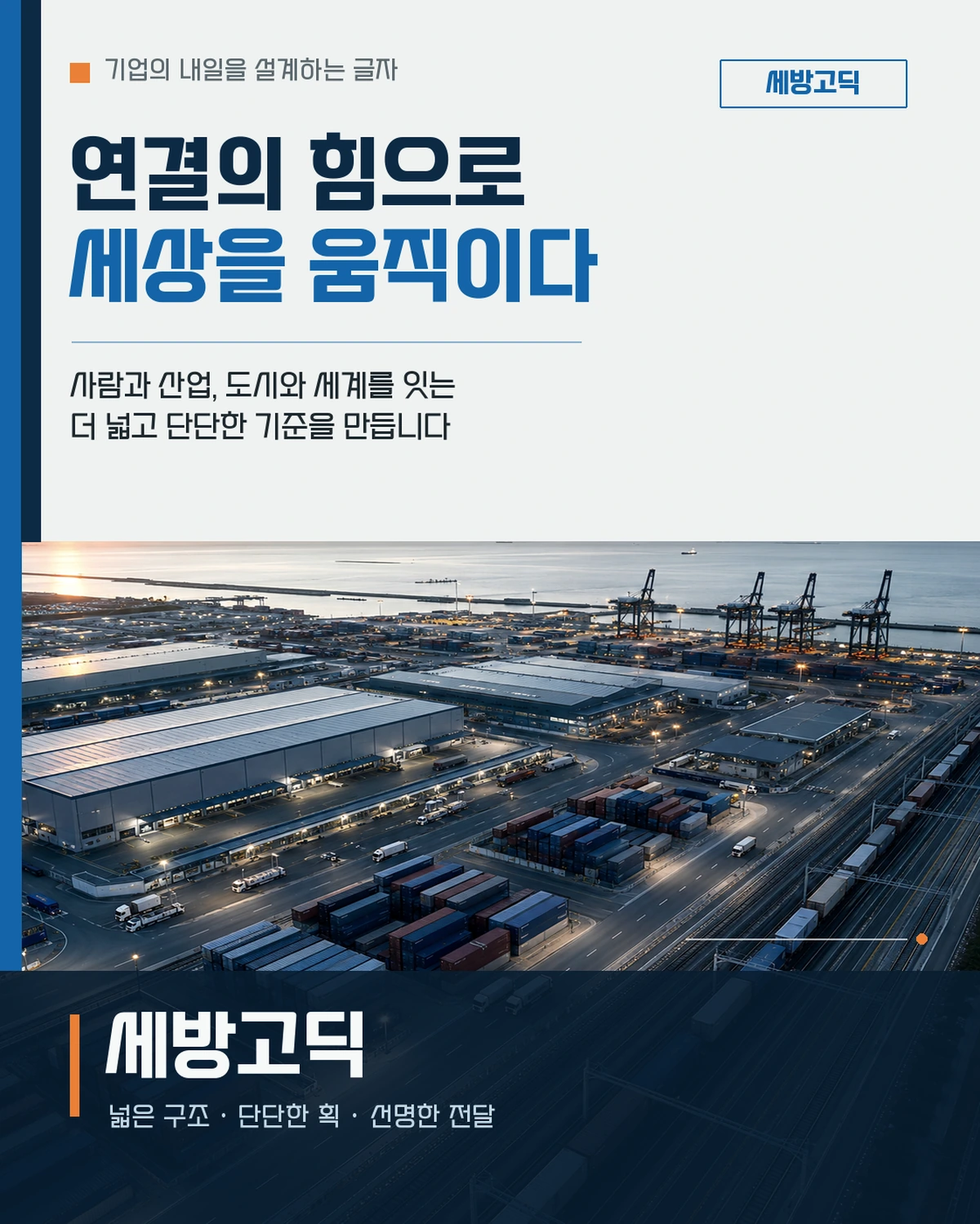
세방고딕 2.0 — 세방그룹에서 배포하는 무료 폰트입니다. Light부터 Bold, 이탤릭까지 갖춘 자면이 큰 네모틀 고딕체
세방그룹이 2020년에 처음 공개한 세방고딕을 다듬어 2026년 9월 2.0으로 새로 내놓았습니다. 기존 정체성은 그대로 두고 실무에서의 완성도와 활용성을 높였다고 밝히고 있습니다.
바뀐 점은 네 가지입니다. 초·중성에 쓰일 때 도드라지던 된자음(ㅆ·ㅉ)의 형태를 다듬었고, 단단한 인상에 섬세함을 더할 Light를 새로 만들었습니다. CI 로고의 기울기에서 출발한 12도 이탤릭과, 스페인어 같은 라틴 문자 언어를 위한 라틴 문자 128자도 더했습니다.
파일에서 재어 보면 받침에 따른 높이 차가 거의 없는 네모틀에 자면을 넉넉히 채워 인상이 단단합니다. 한글 11,172자를 모두 담았고, 세방그룹은 Light를 가벼운 본문에, Regular를 보고서에, Bold를 제목에 권합니다. 인쇄·웹·영상·광고와 CI·BI까지 상업적으로 쓸 수 있지만 폰트 파일의 수정·재배포·재판매는 금지이고, 불법 도박·성인물 같은 용도에는 쓸 수 없습니다.